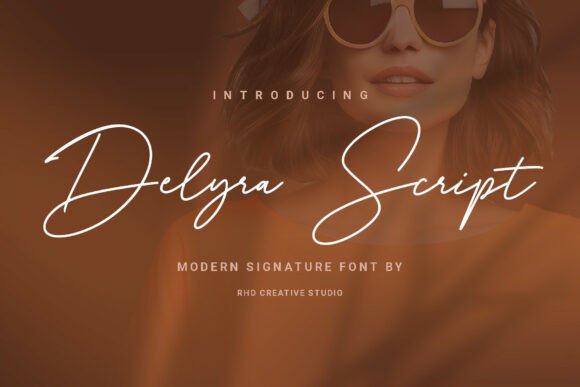
Delyra Script
Encontrar los elementos de diseño adecuados puede ser un desafío, pero Delyra Script ofrece una colección excepcional que eleva tu trabajo al instante.
Elaborado con precisión, Delyra Script proporciona vectores limpios, tipografía suave y una licencia comercial para tu tranquilidad.
Ya sea que estés creando productos POD (impresión bajo demanda), invitaciones de boda o gráficos para redes sociales, Delyra Script es una opción ideal.